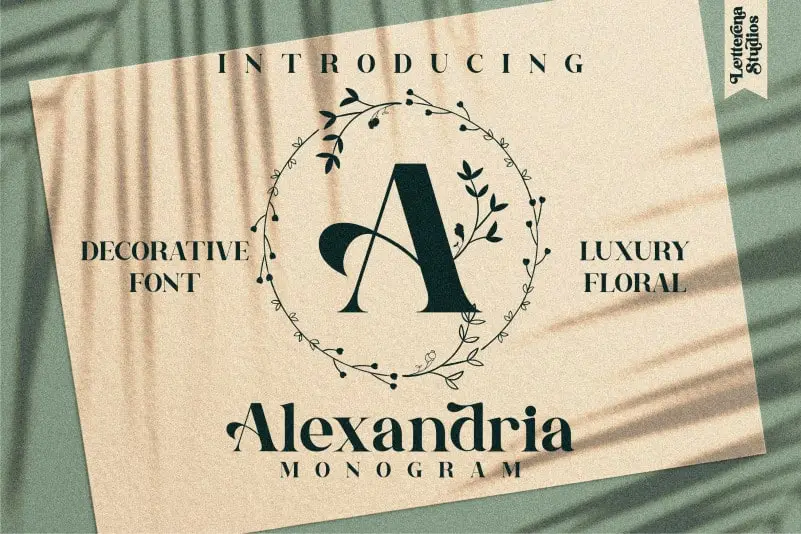
Alexandria Monogram Display Font – Download Grátis
A Alexandria Monogram Display Font é uma elegante fonte decorativa que oferece um toque luxuoso com ornamentos de folhas autênticas e delicadas. Suas formas delicadas podem fazer sua marca brilhar nas criações para festas de casamento, como convites de noivado e cartões de papelaria; são perfeitas para adicionar um toque criativo a postagens em redes sociais que desejam chamarem atenção; e também adicionam charme aos logos e as lembranças de aniversário infantis. Esta fonte é uma escolha ideal para quem busca dar uma personalidade única às suas criações, com seu padrão único que ressoa a elegância e a sofisticação. Seja em um projeto pessoal ou profissional, ela certamente enriquecerá sua visão gráfica.